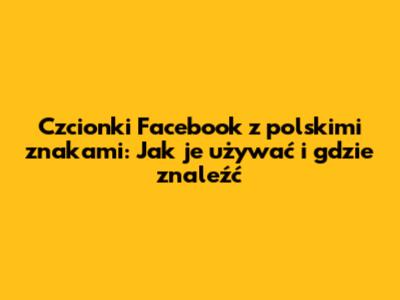
Czcionki Facebook Z Polskimi Znakami
Witajcie, kochani miłośnicy Facebooka! Dzisiaj zagłębimy się w temat, który może wydawać się z pozoru prosty, ale potrafi sprawić sporo kłopotu – polskie znaki w czcionkach na Facebooku. Wiecie, o co chodzi, prawda? Kiedy chcemy napisać coś po polsku, z naszymi pięknymi "ą", "ę", "ć", "ł", "ń", "ó", "ś", "ź", "ż", a nasza wybrana czcionka gdzieś te magiczne literki gubi, zostawiając nam niezrozumiałe znaczki albo co gorsza, kompletnie psując wygląd naszego posta. To frustrujące, kiedy chcemy być kreatywni i użyć jakiejś fajnej, niestandardowej czcionki, a ona nie współpracuje z naszym ojczystym językiem. Ale spokojnie, mam dla Was garść porad, jak sobie z tym poradzić, gdzie szukać tych idealnych fontów i jak sprawić, by Wasze posty na Facebooku zawsze wyglądały profesjonalnie i czytelnie, nawet z tymi wszystkimi ogonkami i kreskami. Pokażemy Wam, jak wybrać czcionki, które bez problemu obsłużą polskie znaki, unikając typowych pułapek i frustracji. Zapnijcie pasy, bo ruszamy w podróż po świecie polskich znaków w internetowych fontach!
Dlaczego polskie znaki są takie ważne w czcionkach?
Zacznijmy od absolutnych podstaw, bo to kluczowe dla zrozumienia problemu. Polskie znaki, czyli te wszystkie urocze "ogonki" i "kreski" dodane do liter alfabetu łacińskiego, są integralną częścią języka polskiego. Bez nich nasze słowa tracą sens, brzmienie, a nawet znaczenie. Pomyślcie sobie o słowie "koń" bez "ó". Brzmi inaczej, prawda? Albo "łąka" bez "ą". To już nie ta sama łąka. Facebook, jako platforma globalna, operuje na wielu językach i systemach kodowania znaków. Kiedy tworzymy treść, która ma być zrozumiała dla polskich odbiorców, nie możemy bagatelizować znaczenia prawidłowego wyświetlania tych specyficznych liter. Problemy z polskimi znakami w czcionkach na Facebooku wynikają najczęściej z tego, że dana czcionka po prostu nie została zaprojektowana z myślą o obsłudze wszystkich znaków diakrytycznych języka polskiego. Twórcy fontów, zwłaszcza tych darmowych, często skupiają się na podstawowym alfabecie łacińskim, pomijając bardziej specyficzne znaki. Kiedy Facebook próbuje wyświetlić taki znak, a czcionka go nie posiada, system zazwyczaj zastępuje go domyślnym symbolem, który wygląda jak kwadracik, pytajnik albo coś kompletnie niepasującego. To psuje estetykę, utrudnia czytanie i może sprawić, że nasz komunikat zostanie odebrany jako nieprofesjonalny lub lekceważący. Dlatego tak ważne jest, aby świadomie wybierać czcionki obsługujące polskie znaki, dbając o to, by nasza komunikacja była jasna, poprawna i po prostu ładna. To nie tylko kwestia estetyki, ale przede wszystkim funkcjonalności i szacunku dla języka oraz odbiorcy.
Gdzie szukać czcionek na Facebooka z polskimi znakami?
Wielu z Was pewnie zastanawia się teraz: gdzie w ogóle znaleźć takie czcionki, które są przyjazne dla polskich znaków i jednocześnie świetnie wyglądają na Facebooku? Dobra wiadomość jest taka, że jest ich całkiem sporo, tylko trzeba wiedzieć, gdzie szukać. Najlepszym miejscem do rozpoczęcia poszukiwań są strony z darmowymi fontami, które często posiadają filtry lub opisy wskazujące na wsparcie dla różnych języków. Jedną z najpopularniejszych i najbardziej godnych zaufania platform jest Google Fonts. To ogromna biblioteka, w której znajdziecie mnóstwo fantastycznych, darmowych czcionek, a co najważniejsze – większość z nich ma doskonałe wsparcie dla języków europejskich, w tym polskiego. Jak to sprawdzić? Wystarczy wejść na stronę Google Fonts, wybrać interesującą Was czcionkę, a następnie w sekcji "Character Map" lub podobnej (czasem trzeba przewinąć w dół do "About" lub "Details") poszukać informacji o obsługiwanych językach lub po prostu zobaczyć, czy na mapie znaków znajdują się nasze polskie "ą, ę, ć, ł, ń, ó, ś, ź, ż". Zazwyczaj jest tam wyraźne oznaczenie "Latin Extended" lub bezpośrednie wymienienie języków, które dana czcionka obsługuje. Inne świetne źródła to Font Squirrel czy DaFont. Na DaFont trzeba być trochę bardziej czujnym, bo tam znajdziemy zarówno fonty z pełnym wsparciem, jak i te bardziej "artystyczne", które mogą mieć braki. Zawsze sprawdzajcie opisy i podglądy. Kiedy znajdziecie potencjalnie fajną czcionkę, spróbujcie napisać w podglądzie kilka polskich słów, zawierających znaki diakrytyczne. Jeśli widzicie "kwadraciki", to znak, że font odpada. Pamiętajcie też, że nie każda czcionka musi być od razu super ozdobna. Czasem proste, eleganckie fonty z Google Fonts, jak Open Sans, Lato czy Montserrat, są najlepszym wyborem, bo są wszechstronne i gwarantują poprawne wyświetlanie polskich znaków. Niektórzy użytkownicy korzystają też z generatorów czcionek online, które pozwalają stworzyć tekst w wybranej stylistyce, a następnie skopiować go jako obrazek lub tekst. Należy jednak pamiętać, że Facebook nie lubi, gdy treści są wyłącznie obrazkami, więc lepiej stawiać na tekst, który jest indeksowalny. Podsumowując, klucz do sukcesu to Google Fonts, uważne czytanie opisów i testowanie czcionek na polskich znakach przed ich użyciem.
Jak używać generatorów czcionek z polskimi znakami na Facebooku?
No dobra, mamy już źródła, ale jak faktycznie używać tych generatorów czcionek na Facebooku, żeby nasze posty wyglądały mega stylowo i jednocześnie były w pełni czytelne dla wszystkich Polaków? To prostsze niż myślicie, ale wymaga kilku kroków i zrozumienia, jak to wszystko działa. Przede wszystkim, musicie wiedzieć, że Facebook sam w sobie nie oferuje nam zmiany czcionki bezpośrednio w edytorze postów czy komentarzy. Oznacza to, że aby użyć niestandardowej czcionki, musimy ją sobie najpierw przygotować gdzie indziej, a potem wkleić na Facebooka. I tu właśnie wchodzą do gry generatory czcionek online. Działają one na zasadzie konwersji Waszego tekstu na specjalne znaki Unicode, które różne przeglądarki i systemy potrafią wyświetlić jako litery w niestandardowych krojach. Popularne generatory znajdziecie wpisując w Google frazy typu "facebook font generator", "generator czcionek", "fancy text generator" czy "tekst po polsku z ogonkami". Po wejściu na taką stronę, wystarczy wpisać tekst, który chcecie opublikować, a generator od razu pokaże Wam różne warianty Waszego tekstu w innych czcionkach. Ważne jest, aby wybrać generator, który wyraźnie zaznacza, że obsługuje polskie znaki diakrytyczne. Nie wszystkie generatory są takie same! Niektóre mogą wyświetlać poprawne "ą", "ę", "ć" itd., inne znów potrafią spsocić sprawę i zamienić je na dziwne symbole. Zawsze, ale to zawsze, przetestujcie efekt na sobie, wpisując zdanie z polskimi znakami, zanim skopiujecie je na Facebooka. Kiedy znajdziecie już idealną wersję, po prostu ją zaznaczacie i kopiujecie (Ctrl+C lub kliknięcie prawym przyciskiem myszy i "Kopiuj"). Następnie przechodzicie do okna tworzenia posta, komentarza czy wiadomości na Facebooku i wklejacie skopiowany tekst (Ctrl+V lub kliknięcie prawym przyciskiem i "Wklej"). Po wklejeniu, Wasz tekst powinien pojawić się w tej wybranej, nietypowej czcionce. Pamiętajcie, że choć te generatory są super dla podkreślenia czegoś, dodania stylu czy zwrócenia uwagi, to nie powinniście używać ich do pisania całych długich tekstów. Dłuższe fragmenty w niestandardowych czcionkach mogą być trudniejsze do przeczytania dla niektórych użytkowników, a także gorzej indeksowane przez wyszukiwarki. Najlepiej sprawdzają się jako ozdobniki w nagłówkach, krótkich hasłach, komentarzach czy wiadomościach prywatnych. Upewnijcie się też, że czcionka, którą wybieracie z generatora, jest rzeczywiście czytelna i nie wygląda jak maziaje. Dobrej zabawy z eksperymentowaniem!
Najlepsze czcionki dla Facebooka z obsługą polskich znaków
Chcąc tworzyć angażujące i estetyczne treści na Facebooku, często sięgamy po niestandardowe czcionki, aby wyróżnić nasz profil czy posty. Ale jak wybrać te najlepsze, które będą jednocześnie stylowe i bezproblemowo wyświetlą nasze ukochane polskie znaki? Spokojnie, mam dla Was kilka sprawdzonych typów, które sprawią, że Wasze teksty będą wyglądać świetnie, bez żadnych nieprzyjemnych niespodzianek. Google Fonts to zdecydowanie złoto i tam znajdziecie najwięcej pewniaków. Zacznijmy od klasyków, które nigdy nie zawodzą: Open Sans. To niezwykle popularna, bezszeryfowa czcionka, która jest idealna do wszelkich zastosowań. Jest bardzo czytelna, przyjazna dla oka i ma fantastyczne wsparcie dla polskich znaków. Kolejny mocny zawodnik to Lato. Również bezszeryfowa, nieco bardziej zaokrąglona niż Open Sans, dodaje tekstom ciepła. Jest równie wszechstronna i bez problemu obsłuży nasze "ą, ę, ć". Nie można też zapomnieć o Montserrat. To czcionka inspirowana starymi plakatami z Buenos Aires, ma trochę bardziej geometryczny charakter, ale jest nadal bardzo czytelna i doskonale radzi sobie z polskimi znakami. Jeśli szukacie czegoś z szeryfami, co nada Waszym tekstom elegancji i klasyki, polecam Merriweather. Jest to czcionka z wyraźnymi szeryfami, która świetnie wygląda w dłuższych tekstach, a przy tym bez problemu wyświetla wszystkie polskie znaki. Dla tych, którzy lubią odrobinę więcej charakteru, ale nadal chcą zachować czytelność i wsparcie dla polskich znaków, dobrym wyborem może być Playfair Display. To elegancka czcionka szeryfowa, idealna do tytułów i krótkich, efektownych fragmentów. Pamiętajcie, że kluczem jest nie tylko wygląd, ale przede wszystkim kompatybilność z polskimi znakami. Zawsze, kiedy pobieracie nową czcionkę, upewnijcie się, że w jej opisie jest informacja o obsłudze języków europejskich (Latin Extended) lub po prostu przetestujcie ją w jakimś generatorze tekstu, wpisując zdania z naszymi specyficznymi literami. Wybierając te sprawdzone fonty, macie pewność, że Wasze posty na Facebooku będą wyglądać profesjonalnie i nienagannie, niezależnie od tego, czy piszecie "żółć" czy "pięćdziesiąt". Z tymi narzędziami i wiedzą, możecie śmiało eksperymentować z wyglądem swoich treści i cieszyć się ich nienaganną prezentacją! Gwarantuję Wam, że użycie tych fontów sprawi, że Wasze profile nabiorą nowego, lepszego wyrazu.
Jak uniknąć problemów z polskimi znakami w postach na Facebooku?
Hej, ekipa! Czasami zdarza się, że mimo naszych najlepszych chęci, polskie znaki na Facebooku płata nam figle, prawda? Post, który miał być stylowy, nagle wygląda jak napisany przez obcokrajowca po trzech kawach, bo zamiast "ę" mamy "?" albo jakieś inne dziwne symbole. Ale nie martwcie się, mam dla Was kilka super sprawdzonych sposobów, jak tych irytujących błędów unikać i zawsze prezentować się z najlepszej strony. Po pierwsze, zasada numer jeden, którą powtarzam jak mantrę: Zawsze sprawdzajcie czcionkę przed użyciem! Niezależnie od tego, czy korzystacie z generatora, czy pobieracie font na swój komputer, poświęćcie chwilę na test. Wpiszcie zdanie zawierające wszystkie polskie znaki: "Pójdźże, łódką napełnij źrenicę!”. Jeśli wszystkie litery "ą, ę, ć, ł, ń, ó, ś, ź, ż" wyświetlają się poprawnie, to macie zielone światło. Jeśli widzicie "kwadraciki", pytajniki lub inne dziwactwa, odpuśćcie sobie tę czcionkę na Facebooka – nie jest warta Waszej frustracji. Po drugie, stawiajcie na sprawdzone źródła. Jak już wspominałem, Google Fonts to Wasz najlepszy przyjaciel. Fonty stamtąd są projektowane z myślą o globalnym zasięgu i zazwyczaj mają świetne wsparcie dla języków europejskich. Unikajcie pobierania czcionek z przypadkowych stron, które mogą nie zapewniać odpowiedniej jakości. Po trzecie, nie przesadzajcie z ozdobnikami. Pamiętajcie, że Facebook to platforma do szybkiej komunikacji. Chociaż fajnie jest użyć nietypowej czcionki do nagłówka czy ważnego komunikatu, to pisanie całych postów w ozdobnych, trudnych do czytania fontach jest złym pomysłem. Może to zniechęcić odbiorców, utrudnić czytanie, a nawet wpłynąć na zasięgi posta, bo algorytmy mogą mieć problem z jego przetworzeniem. Trzymajcie się zasady: styl tak, ale czytelność przede wszystkim. Po czwarte, używajcie narzędzi mądrze. Generatory czcionek są świetne, ale pamiętajcie, że konwertują tekst na specjalne znaki Unicode. Upewnijcie się, że generator, którego używacie, faktycznie poprawnie obsługuje polskie znaki. Czasami lepiej wybrać prostszy, ale pewniejszy font z Google Fonts i wkleić go bezpośrednio, niż ryzykować z generatora, który może namieszać. Po piąte, dbajcie o aktualizacje. Czasem problemy mogą wynikać ze starych wersji przeglądarek lub systemu. Upewnijcie się, że Wasze oprogramowanie jest aktualne. Stosując się do tych prostych zasad, możecie mieć pewność, że Wasze posty na Facebooku zawsze będą wyglądać profesjonalnie, bez nieestetycznych znaczków zamiast polskich liter. Dbajcie o detale, a Wasi odbiorcy na pewno to docenią! Pamiętajcie, że dobra komunikacja to podstawa, a czytelny i poprawny tekst to jej kluczowy element. Nie pozwólcie, by fonty zepsuły Wasz przekaz!
Podsumowanie: Ciesz się stylowymi postami z polskimi znakami!
I tak oto dobrnęliśmy do końca naszej małej podróży po świecie czcionek Facebook z polskimi znakami. Mam nadzieję, że teraz czujecie się pewniej i wiecie, jak sprawić, by Wasze posty, komentarze czy wiadomości na tej popularnej platformie wyglądały nie tylko stylowo, ale przede wszystkim były w pełni czytelne i poprawne językowo. Pamiętajcie, że kluczem jest świadomy wybór fontów, które natywnie wspierają nasz piękny język polski, ze wszystkimi jego urokliwymi "ogonkami" i "kreskami". Google Fonts to niezawodne źródło, które oferuje ogromną bazę wysokiej jakości, darmowych czcionek, które zazwyczaj świetnie radzą sobie z polskimi znakami. Zawsze warto tam zaglądać i wybierać sprawdzone kroje, takie jak Open Sans, Lato czy Montserrat, które są wszechstronne i bezpieczne. Jeśli jednak macie ochotę na coś bardziej nietypowego, generatory czcionek online mogą być świetnym narzędziem, ale z nimi trzeba postępować ostrożnie. Zawsze testujcie efekt końcowy na sobie, wpisując zdania z polskimi znakami, i upewnijcie się, że generator, którego używacie, faktycznie poprawnie je wyświetla. Unikajcie fontów, które zastępują polskie znaki dziwnymi symbolami, bo to tylko psuje odbiór Waszych treści. Nie zapominajcie też o umiarze – najlepsze czcionki to te, które są czytelne. Ozdobne fonty świetnie nadają się do nagłówków czy krótkich komunikatów, ale całe długie teksty lepiej pisać standardowymi, sprawdzonymi krojami. Stosując się do tych prostych zasad, możecie tworzyć unikalne i estetyczne treści na Facebooku, które przyciągną uwagę i zostaną pozytywnie odebrane przez Waszych odbiorców. Bo przecież chodzi o to, żeby komunikacja była nie tylko efektywna, ale i przyjemna dla oka, prawda? Mam nadzieję, że te wskazówki okażą się dla Was przydatne i pozwolą Wam śmielej eksperymentować z wyglądem Waszych internetowych wypowiedzi. Bawcie się dobrze i twórzcie piękne posty, które zawsze będą się wyróżniać! Powodzenia na Facebooku, drodzy czytelnicy!